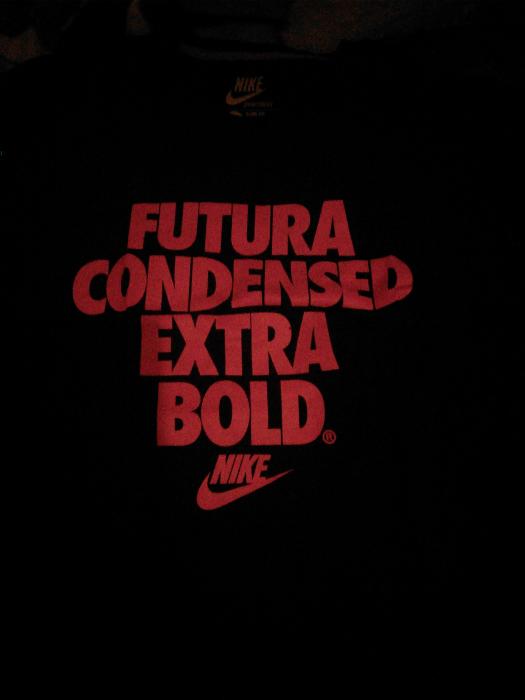
Ähnliche Schrift wie bei Nike gesucht
ich bin auf der suche, nach einer ähnlichen Schrift wie Nike sie vewendet. Sie sollte serifenlos und Fett sein.
Anbei der Link zu Nike
Eine weitere Frage, verwendet Nike auf seiner Seite überall die gleiche Schriftart in nur unterschiedlicher Größe?
Auf nike.com/de werden drei Schriften verwendet: Futura für RUN FOREVER; Trade Gothic für Überschriften, Knöpfe etc. (alles, was in GROẞBUCHSTABEN geschrieben wird); Helvetica für den Rest.